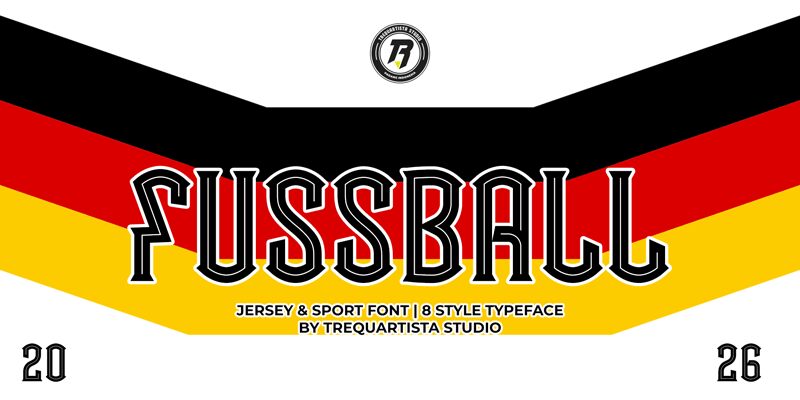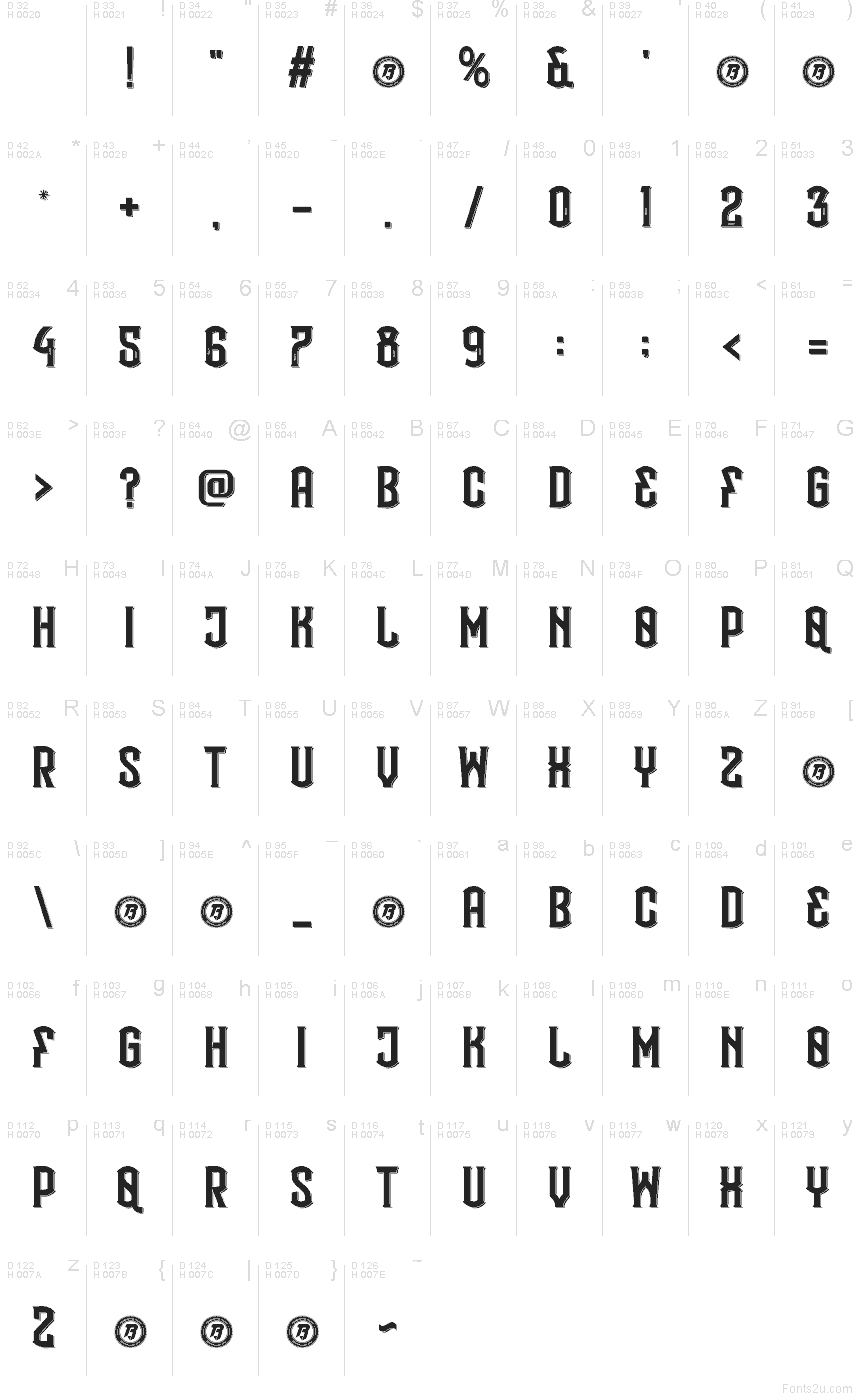
Fussball 4 de Trequartista Studio es una tipografía gótica moderna en mayúsculas, con ese aire contundente de los clubes de antaño. Sus letras conservan la esencia blackletter, pero con formas depuradas y gráficas: muescas profundas, uniones angulosas y curvas amplias que hacen que parezca cortada sobre pancartas en lugar de escrita a mano.
Encaja a la perfección en branding deportivo, carteles de pubs, titulares de pósteres, merchandising de equipos, portadas de discos y rótulos donde busques un toque histórico auténtico sin caer en el exceso decorativo medieval. Las mayúsculas funcionan especialmente bien en nombres cortos y monogramas, ya que los arcos repetidos y los cortes angulares otorgan a cualquier palabra un ritmo compacto, similar al de una insignia.